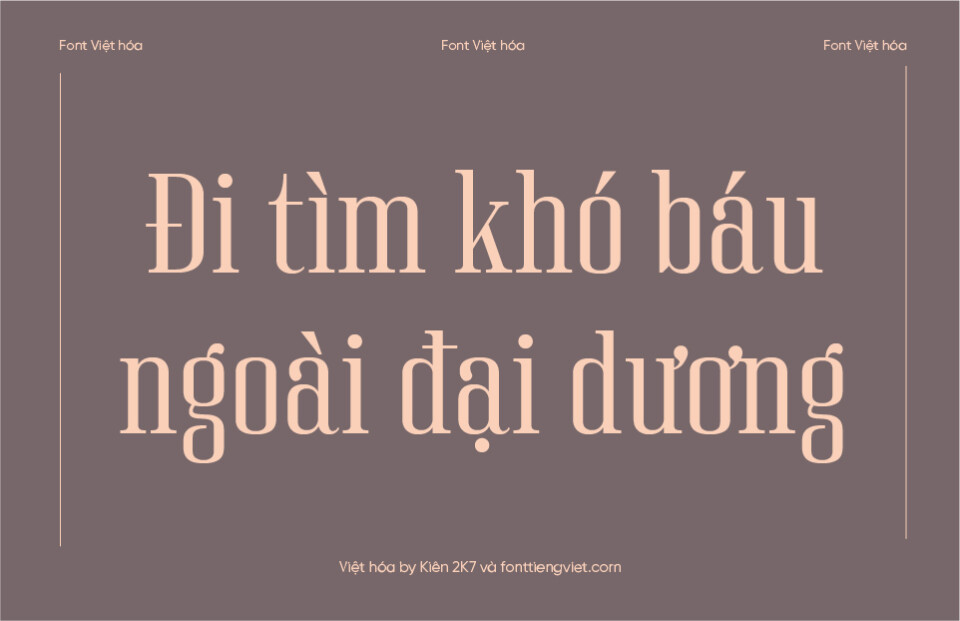
Font Việt hóa 1FTV Rinella Regular – Lựa chọn tinh tế cho thiết kế hiện đại
Trong thế giới đồ họa hiện nay, việc tìm kiếm một bộ Font Chữ đẹp mắt và hỗ trợ đầy đủ tiếng Việt là ưu tiên hàng đầu của nhiều bạn học sinh và nhà thiết kế. Font Việt hóa 1FTV Rinella Regular nổi lên như một giải pháp hoàn hảo, kết hợp giữa nét thanh lịch cổ điển và sự tối giản đương đại. Bộ font này không chỉ giúp các bài thuyết trình trở nên chuyên nghiệp hơn mà còn mang lại cảm hứng sáng tạo mạnh mẽ cho người sử dụng trong mọi dự án học tập hay công việc cá nhân.
Đặc điểm nổi bật của Font Việt hóa 1FTV Rinella Regular
Thiết kế chữ cái cân đối và dễ đọc
Đặc trưng lớn nhất của Font Việt hóa 1FTV Rinella Regular chính là cấu trúc các ký tự được tính toán tỉ mỉ với tỷ lệ vàng. Các đường nét vừa phải, không quá dày cũng không quá mỏng, giúp người xem dễ dàng tiếp nhận nội dung ngay cả ở kích thước nhỏ. Đây là yếu tố cực kỳ quan trọng khi trình bày văn bản dài hoặc làm tiêu đề cho các báo cáo trong nhà trường.
Khả năng tương thích đa dạng
Ứng dụng thực tế và cách sở hữu font chữ
Nhờ vẻ ngoài hiện đại, Font Việt hóa 1FTV Rinella Regular thường được ứng dụng trong thiết kế thiệp mời, bìa sách, và đặc biệt là các ấn phẩm truyền thông học đường. Để có được những sản phẩm ưng ý, người dùng nên kết hợp font này với các tông màu trung tính hoặc pastel để tôn vinh sự tinh tế vốn có của nó. Nếu bạn đang tìm kiếm Font Miễn Phí, Font Việt Hóa, Font Việt hóa 1FTV Rinella Regular để làm phong phú thêm kho tài nguyên của mình, hãy nhanh tay trải nghiệm ngay hôm nay để thấy sự khác biệt rõ rệt trong từng khung hình thiết kế.